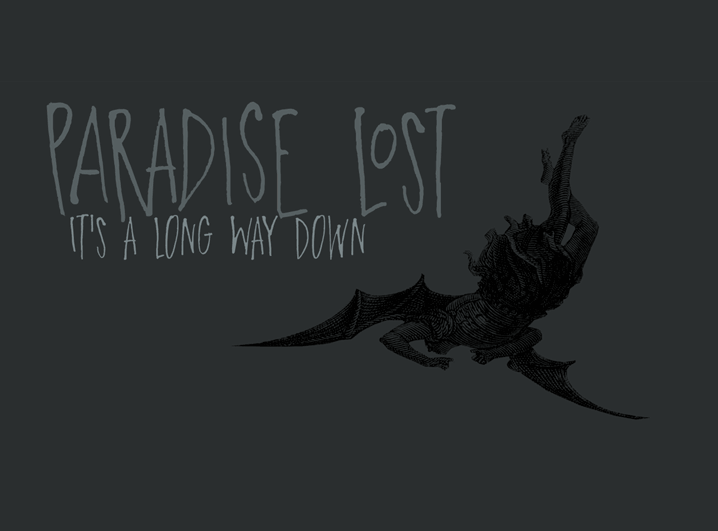
DK Paradise Lost Font é uma fonte leve e colorida projetada para a categoria Playful Fonts. Desenvolvida por Hamilton, esta fonte traz um toque descontraído à sua designação de jogos, aplicativos ou software. Para uso pessoal gratuito, está disponível sem muitas funcionalidades adicionais. Porém, se você pretende usá-la comercialmente em jogos, apps ou softwares, precisa comprar o pacote completo que inclui kerning (ajustes entre as letras para um visual mais harmonioso), direitos de embedding (permite a inclusão da fonte em sites ou aplicativos sem ter que baixar a fonte novamente) e todos os símbolos, inclusive o 4. Embora não seja permitida sua utilização em jogos, apps ou softwares, se você deseja usar esta fonte dessa forma, pode fazê-lo comprando uma licença diretamente no site do designer, www.hanodedfonts.com. Além disso, há um arquivo FAQ incluído que explica mais detalhadamente sobre as condições de uso desta fonte.